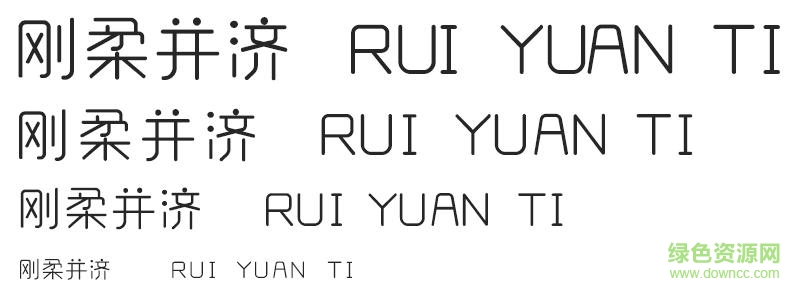
印品睿圓體是一款有印品字體出品的圓體字體,將字體中的點(diǎn)換成圓點(diǎn),讓字形更加豐富,更富有樂趣、美觀。歡迎大家來綠色資源網(wǎng)踴躍下載使用!
印品睿圓體,保留了拐角處呈弧形的圓體特點(diǎn),在字中加入了圓點(diǎn)設(shè)計(jì),并且在筆畫的走向、粗細(xì)及下筆輕重的制作上進(jìn)行了精心處理,使字體看上去更鮮活、靈動(dòng),即保證了美觀程度,又不失時(shí)尚感。